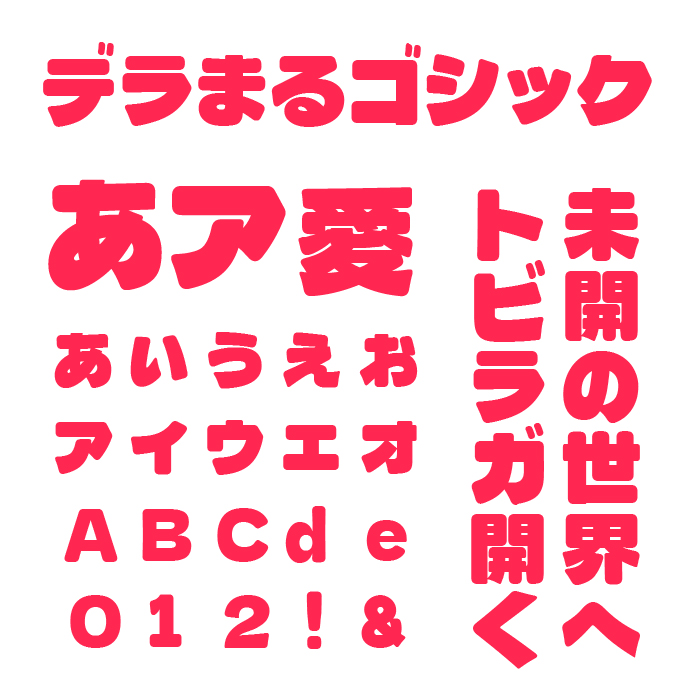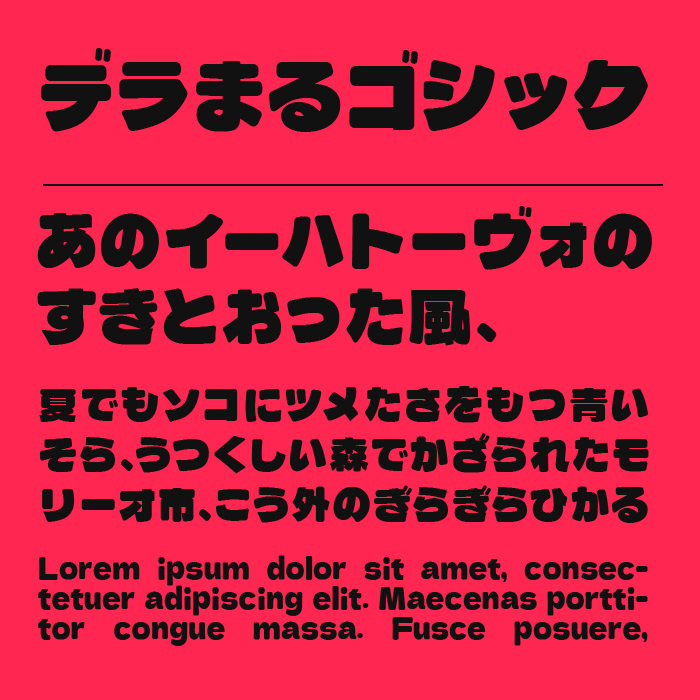
「デラまるゴシック」フォントは、見るだけで元気が湧いてくるような極太ウェイトの丸ゴシック体です。
デラゴシックフォントをベースとして、ずっしりとした太さと、柔らかな丸みが特徴で、インパクトと親しみやすさを同時に伝えることができるフォントです。とくに仮名のフォルムはユーモラスで、ポップな表現や子ども向けのデザイン、イベント系のチラシにもぴったりです。
文字の密度が高く、見出しやタイトルで目を引く効果は抜群です。太さがある分、文字のバランスにも工夫があり、画面越しでも読みやすさがしっかりと保たれています。楽しさと力強さを兼ね備えた、明るく存在感のあるフォントです。
フォントの文字見本